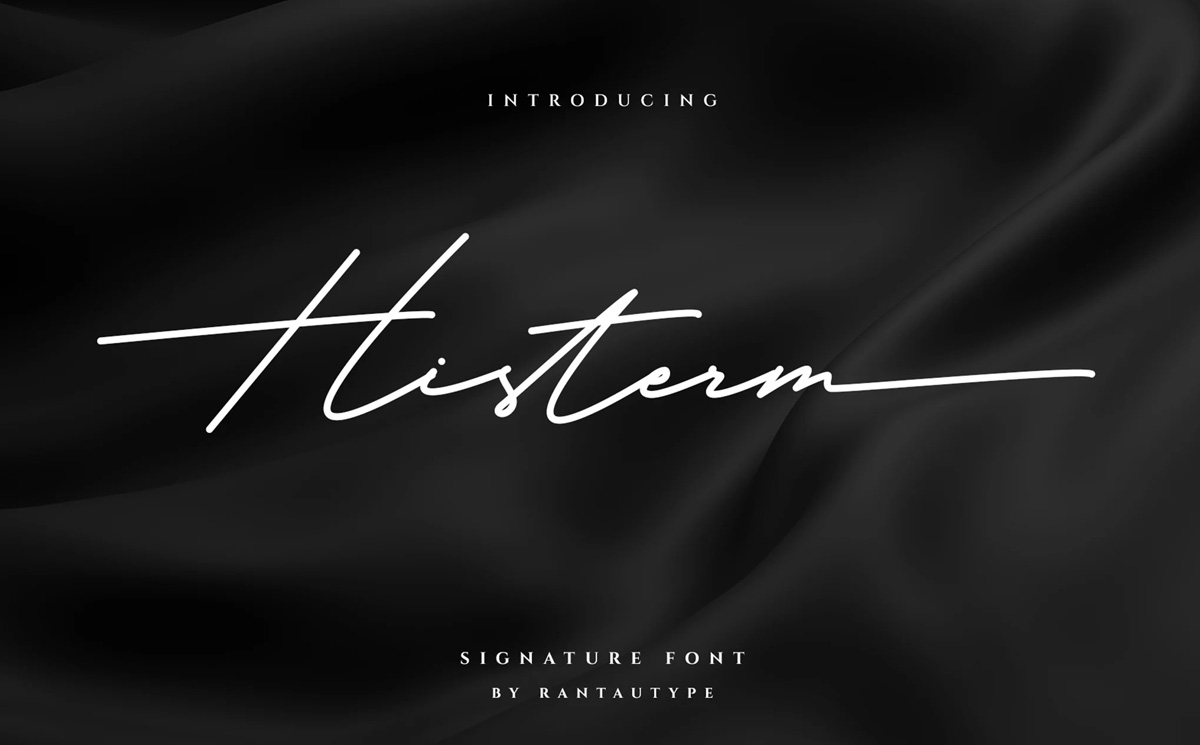
Font Chữ TH Histerm Việt Hóa – Phong Cách Chữ Ký Mềm Mại, Tinh Tế
Tác giả Yudi Pratama Chandra
TH Histerm là một font chữ chữ ký (signature script) hiện đại, được thiết kế bởi Yudi Pratama Chandra – nhà thiết kế đến từ Rantautype Studio. Phông chữ này mang phong cách viết tay bay bổng, với các đường nét mềm mại, uyển chuyển, tạo nên cảm giác cá nhân hóa, sang trọng và đầy cảm xúc.
Toàn bộ hệ thống chữ trong Histerm được mô phỏng theo nét bút mực của chữ ký thật, với độ nghiêng nhẹ sang phải, giúp truyền tải cảm giác chuyển động tự nhiên, như thể từng nét chữ đang tuôn chảy từ tay người viết.
Các ký tự được thiết kế với tỷ lệ cao thấp linh hoạt, đặc biệt ở phần đuôi chữ như “y”, “g”, “f”, “h”… được kéo dài và uốn lượn đầy nghệ thuật – tạo nên vẻ đẹp phóng khoáng, tự do mà vẫn đầy kiểm soát.
Nét chữ giữ ở mức trung tính, không quá thanh cũng không quá đậm, rất lý tưởng cho các thiết kế đòi hỏi sự tinh tế như logo thương hiệu, bao bì mỹ phẩm, watermark ảnh hay chữ ký số cá nhân.